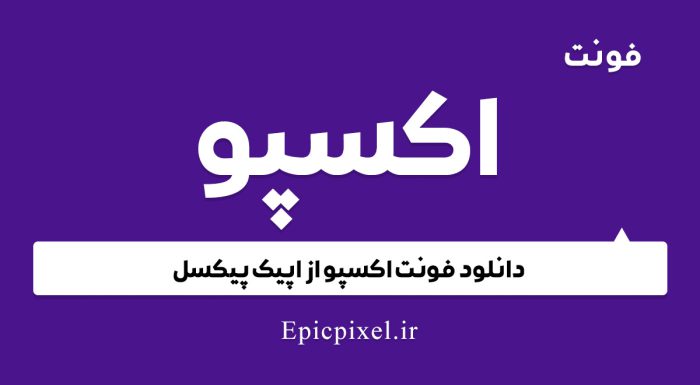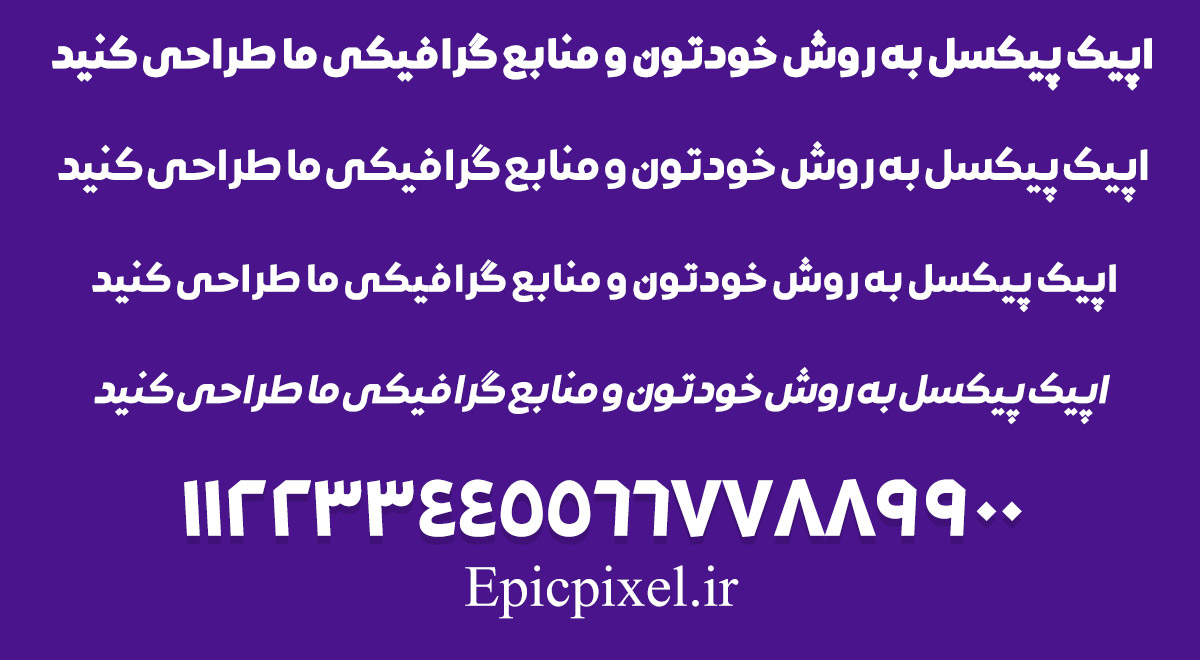
فونت اکسپو فارسی
سلام. خسته نباشید. این فونت همون فونت دیما اکسپو نیست؟ طراح فونت راضی هستن از اینکه شما فونتشونو با تغییر نام، رایگان منتشر کردید؟ ممنون میشم اگر اشتباه میکنم سریعتر بهم اطلاع بدید…
اول اینکه هیچ تغییر نامی صورت نگرفته داخل توضیحات محصول اسم فایل ذکر شده که دیما اکسپو هست
چقدر هم شبیه فونت نمایشگاه بین المللی هستش آفرین